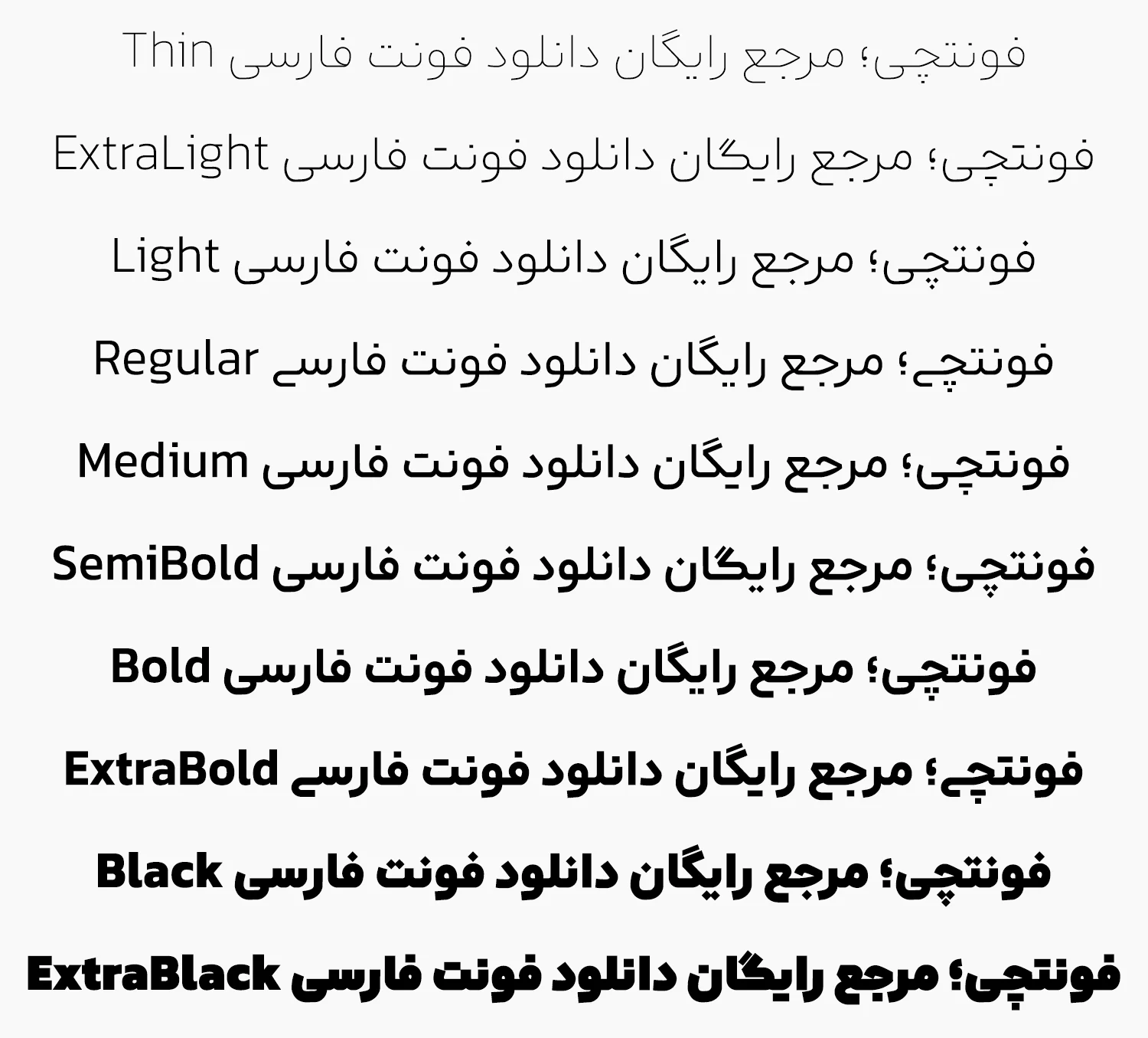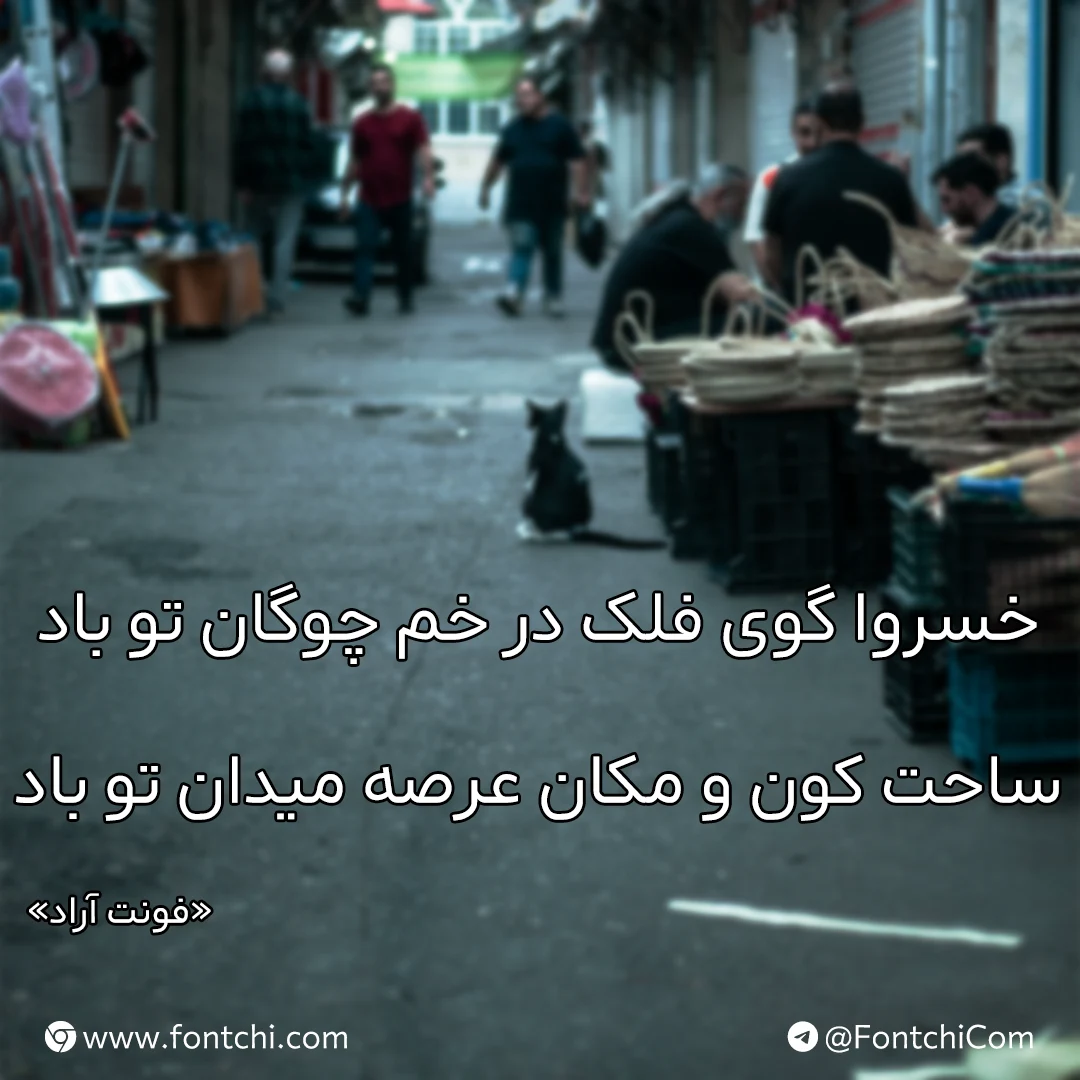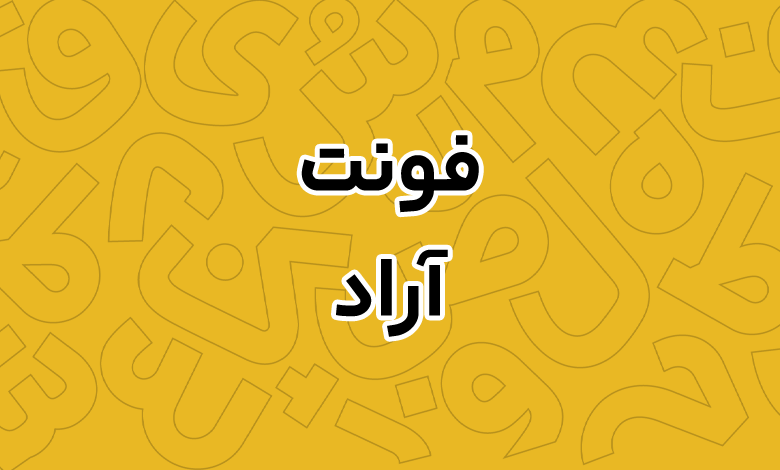
فونت آراد (Arad)
فونت آراد (به انگلیسی: آراد) از سری فونتهای آزاد و رایگان هندسی با ساختار سنس است که در ادامه پروژه فونت شبنم (اثر زندهیاد صابر راستیکردار) طراحی شده است. این فونت از ۱۰ وزن متنوع پشتیبانی میکند که میتوانید در متون بلند و کوتاه از آن استفاده کنید.
محمد درویشی این فونت را با الهام از فونت شبنم طراحی کرده است. این فونت رایگان از ۳ استایل نقطه مربع گسسته، مربع پیوسته و لوزی پشتیبانی میکند. همچنین دارای نسخه وریبل است که در این نسخه میتوانید برخی حروف مانند «ی* ک، گ» را با تایپ متفاوتی بنویسید.
با دانلود فونت آراد میتوانید ساختار خوانایی به متون بلند خود بدهید. خوانایی این فونت به شدت بالاست که میتواند با توجه به تنوع وزنی بالایی که دارد برای استفاده در متون کتاب، مطبوعات و روزنامه، جلد مجلات و همچنین استفاده در نسخه وب برای طراحی رابط کاربری نیز مناسب باشد.
فونت آراد محدود به زبان فارسی نیست. این فونت از دیگر زبانهای خاورمیانهای مثل عربی و اردو نیز پشتیبانی میکند. تمامی اعراب و کاراکترهای تزئینی روی حروف نیز در همنشینی درستی قرار دارند. برای برخی ترکیبات دوتایی در این زبانها نیز گلیفهای جایگزین خاص تعبیه شده تا ظاهر فونت را نمایشیتر کند.
این فونت برای زبان انگلیسی دارای طراحی اختصاصی نیست. در عوض از یک فونت اپنسورس به نام Kanit برای حروف انگلیسی در آن استفاده شده که ظاهر نزدیکی به این قلم دارد. مزیت استفاده از این فونت این بوده که محدود به زبان انگلیسی نیستید و میتوانید برای سایر زبانها مثل ترکی استانبولی، فرانسه، اسپانیا و ایتالیا که دارای تایپ متفاوتی در برخی حروف انگلیسی هستند استفاده کنید.
این فونت از ساختار Stylish Set برای حروف جایگزین پشتیبانی میکند. در نسخه وریبل فونت که حجم بسیار کمی هم دارد، علاوه بر نصب یک فایل میتوانید به همه وزنها از طریق همین یک فایل دسترسی داشته باشید. این نسخه ۳ سبک نقطهگذاری را که شامل نقطه مربع ناپیوسته، مربع پیوسته و لوزی هستند در اختیار قرار میدهد.
علاوه بر این با استفاده از تغییرات در Stylish Set به کمک برنامههایی مثل فتوشاپ یا با استفاده از دستورات CSS برای نسخه وب، میتوانید تغییرات زیر را اعمال کنید:
- امکان تایپ متفاوت برای حروف «ک، گ» را داشته باشید.
- امکان تایپ متفاوت حرف «ی» پایانی را به صورت کشیده داشته باشید.
- اعداد انگلیسی یا عربی را با تایپ اعداد فارسی بنویسید.
- گلیفهای ریال، تومان و درهم را برای واحد پولی تایپ کنید.
تنوع وزنی بالا در کنار استایلهایی که برای تایپ متفاوت حروف قرار داده، باعث شده تا این فونت برای متون کوتاه تا بلند کاربردی باشد. سبک طراحی آن نیز هندسی است که از خط سنس نیز بهره میبرد. از اینرو چه برای اندازههای کوچک و چه بزرگ ساختاری استاندارد دارد.
تفاوتی ندارد که از این فونت برای متون بلند در سایت استفاده کنید یا اینکه بخواهید از نسخه وریبل آن با تغییر شکل نقطهها به مربع پیوسته و با استفاده از وزنهای سیاهتر مانند Black در عناوین استفاده کنید. این فونت انتخاب خوبی برای طراحی رابط کاربری است که برای همین منظور از فرمتهای WOFF و WOFF2 که نسبت به TTF حجم کمتری دارند پشتیبانی میکند.